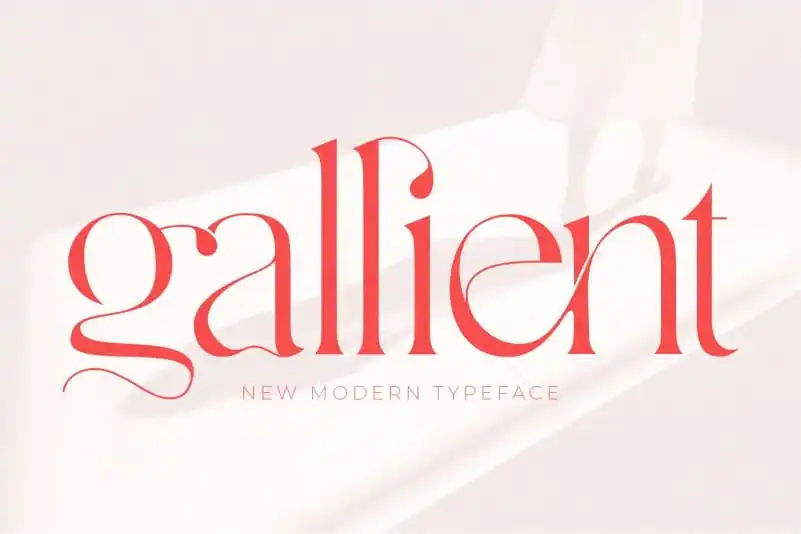
Gallient Serif Font – Fonte Grátis
Gallient Serif Font
A fonte Gallient Serif é uma escolha perfeita para quem busca criar identidades sólidas e carregadas de personalidade. Esta tipografia serifada tem um toque único, ideal para estilos criativos que valorizam a originalidade. A designer dysastudio o criou com cuidado, adaptando cada característica desta fonte para projetos como branding, logotipos, designs de casamentos e até mesmo para postagens nas redes sociais. Suas linhas elegantes e detalhes distintivos tornam-a um recurso inestimável tanto para a criação de produtos em pacote, como etiquetas, como também para gravações em fotografias ou selos. Além disso, suas propriedades versáteis permitem aplicá-la facilmente em cartões de visita, embalagens e outros materiais promocionais – oferecendo um boost poderoso à sua presença digital. Seja qual seja o projeto que está buscando dar uma identidade única e memorable, Gallient Serif Font certamente tem a resposta perfeita para você.